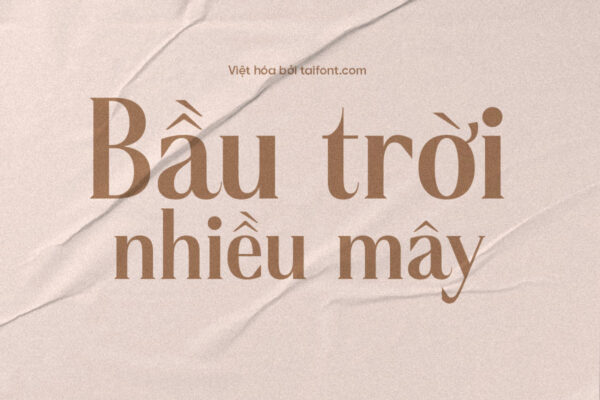
Giới thiệu về Font TF Crestaly Việt hóa
TF Crestaly Việt hóa là một font chữ nổi bật với thiết kế đậm nét và mang đậm phong cách vintage, toát lên vẻ đẹp cổ điển, mạnh mẽ nhưng vẫn đầy tinh tế. Font này gợi nhớ về thời kỳ hoàng kim của typography, với những đường nét chắc chắn và đầy đặn, tạo nên một sự hiện diện mạnh mẽ và cuốn hút. Crestaly là lựa chọn lý tưởng để tạo nên sự độc đáo và ấn tượng cho các thiết kế.
Với đặc điểm nổi bật là độ đậm và phong thái hoài cổ, Crestaly là lựa chọn hoàn hảo cho các thiết kế muốn truyền tải sự mạnh mẽ, sự thật và một chút lãng mạn của thời gian:
- Thiết kế thời trang: Hoàn hảo cho các thương hiệu thời trang cao cấp, đặc biệt là những bộ sưu tập lấy cảm hứng từ phong cách retro, menswear cổ điển hoặc các thiết kế đòi hỏi sự cá tính và mạnh mẽ. Font này có thể dùng trên nhãn mác sản phẩm, lookbook, hoặc các chiến dịch quảng bá, giúp truyền tải vẻ đẹp vượt thời gian và sự độc đáo của trang phục.
- Thiết kế tạp chí: Lý tưởng để sử dụng cho các tiêu đề chính, lời dẫn hoặc các bài viết đặc biệt trong các tạp chí thời trang, nghệ thuật, lịch sử hoặc tạp chí về phong cách sống. Nét đậm và phong cách vintage của Crestaly sẽ làm cho nội dung nổi bật và thu hút độc giả.
- Thiết kế nhận diện thương hiệu: Phù hợp cho các logo hoặc bộ nhận diện thương hiệu muốn truyền tải sự vững chãi, uy tín và một chút hoài cổ đầy phong cách.
Với TF Crestaly Việt hóa, bạn có thể dễ dàng thổi hồn vintage, sự mạnh mẽ và tinh tế vào các thiết kế, tạo ra những sản phẩm không chỉ đẹp mắt mà còn đầy cảm xúc và chiều sâu.
Font Việt hóa TF Crestaly